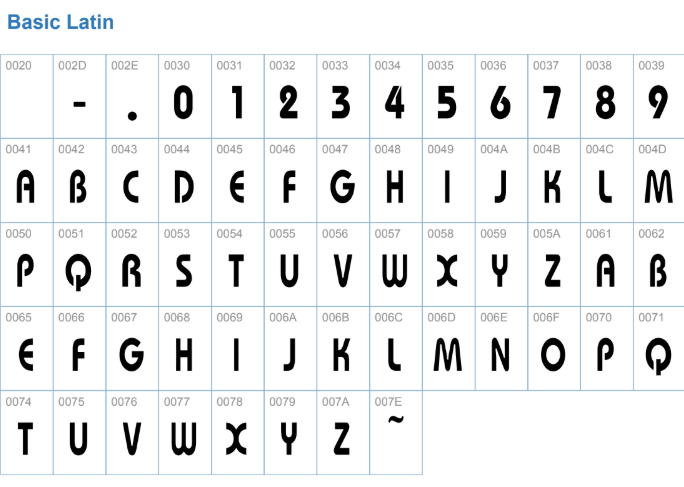
Se existe uma época que define o glamour do futebol mundial, é a era dos “Galácticos”. Entre 2003 e 2005, o Real Madrid não era apenas um time, mas uma constelação desfilando pelos gramados da Europa com o uniforme da Adidas.
Neste post, trazemos para você a tipografia lendária usada por ícones como Zidane, Ronaldo Fenômeno, David Beckham, Figo e Raúl. É a oportunidade perfeita para reproduzir com exatidão as camisas clássicas patrocinadas pela Siemens Mobile que marcaram uma geração.
Estilo Visual e Identidade
A fonte utilizada pela Adidas no início dos anos 2000 para o Real Madrid possui uma estética muito particular. Ela foge do padrão quadrado e aposta em linhas arredondadas e “gordinhas”, com uma presença visual forte nas costas do uniforme branco.
Esta tipografia transmite uma sensação de modernidade (para a época) e fluidez. É impossível olhar para esses números e não lembrar da cobrança de falta do Beckham ou das arrancadas do Ronaldo. A fonte foi usada tanto na La Liga quanto na UEFA Champions League, tornando-se um clássico instantâneo do design esportivo.